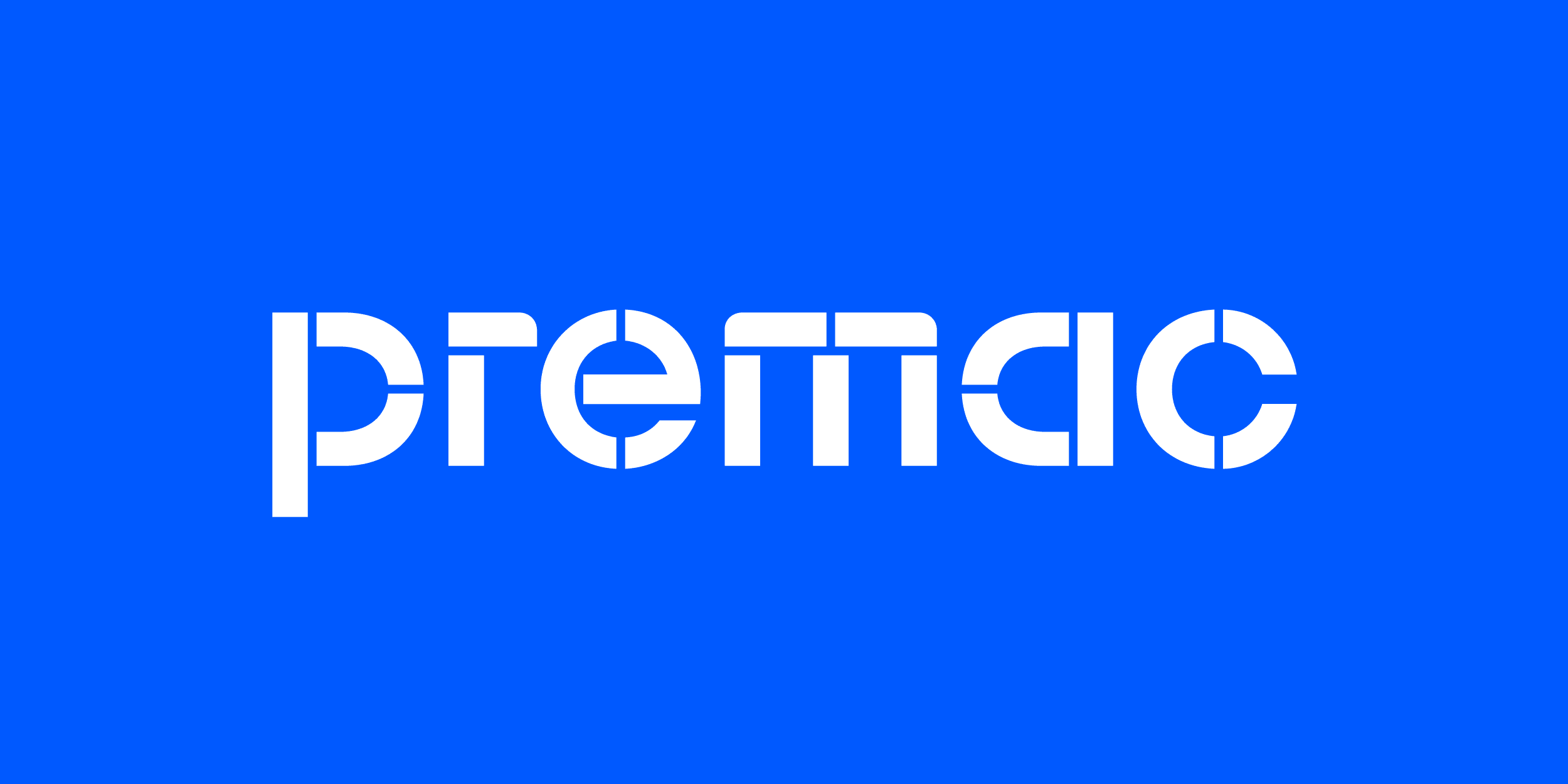
Premac
Logo pre Premac, popredného slovenského výrobcu vonkajšej dlažby.
Modulárne konštruované logo odkazuje na štruktúru dlažby, jeho jednotlivé elementy sú opakovane použité vo viacerých znakoch naprieč logotypom. Vybrané rohy sú zaoblené za účelom zlepšenia čitateľnosti a vyváženia prílišnej technickosti.